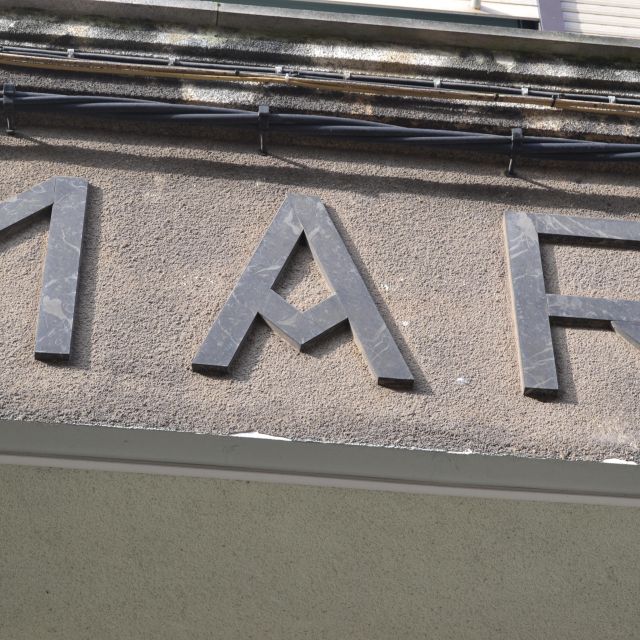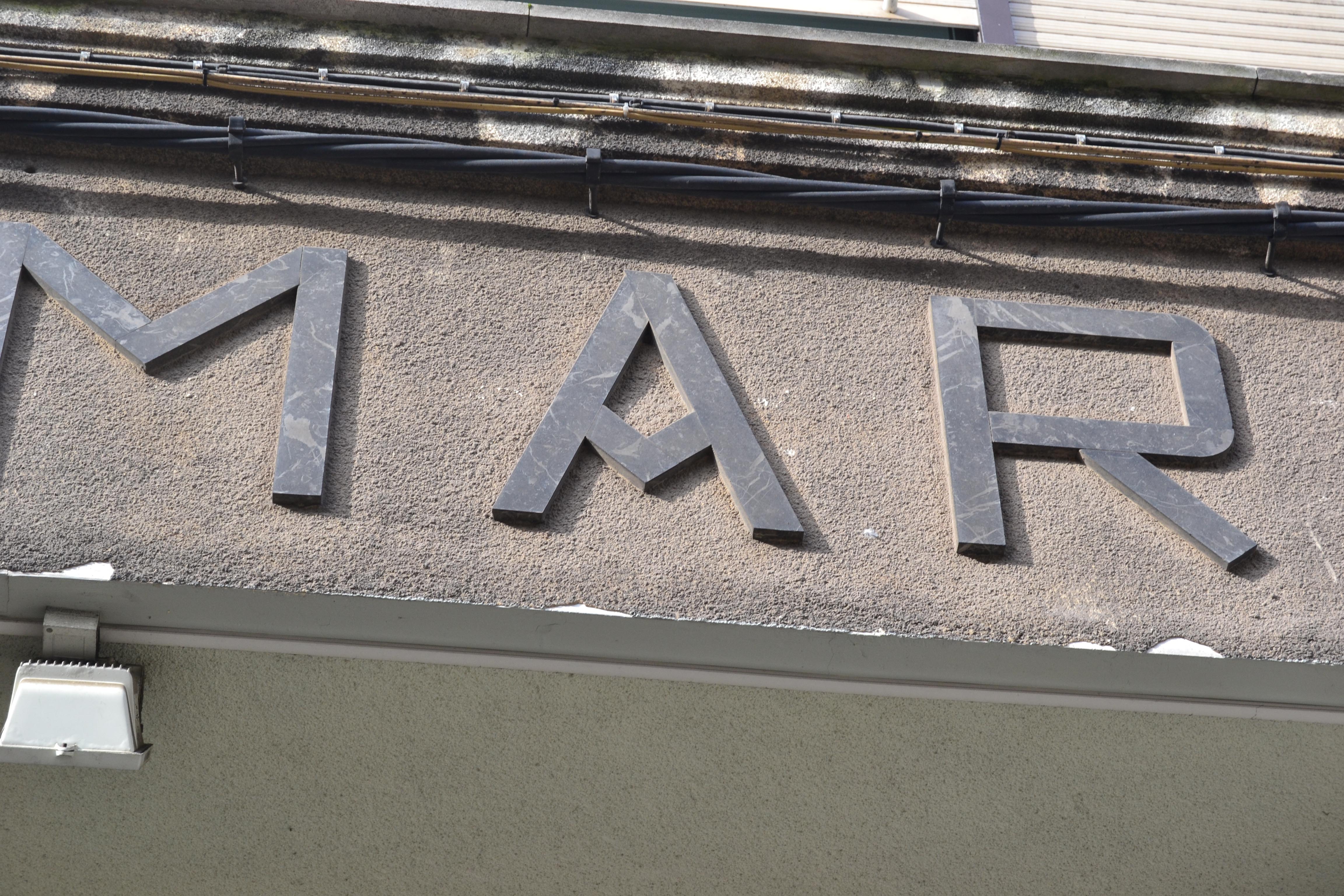
Desconocido
[wyde_info_box title=»Tipografía» icon_set=»typicons» icon_typicons=»typcn typcn-sort-alphabetically»]Geométrica[/wyde_info_box][wyde_info_box title=»Técnica» icon_set=»typicons» icon_typicons=»typcn typcn-brush»]Mármol[/wyde_info_box]
El local que fue la marmolería hoy está ocupado por una Academia. Según nos han dicho los actuales propietarios, durante las obras de acondicionamiento se veían las canalizaciones de desagüe del corte del mármol.
El rótulo fue eliminado durante la remodelación de la fachada a finales de 2014